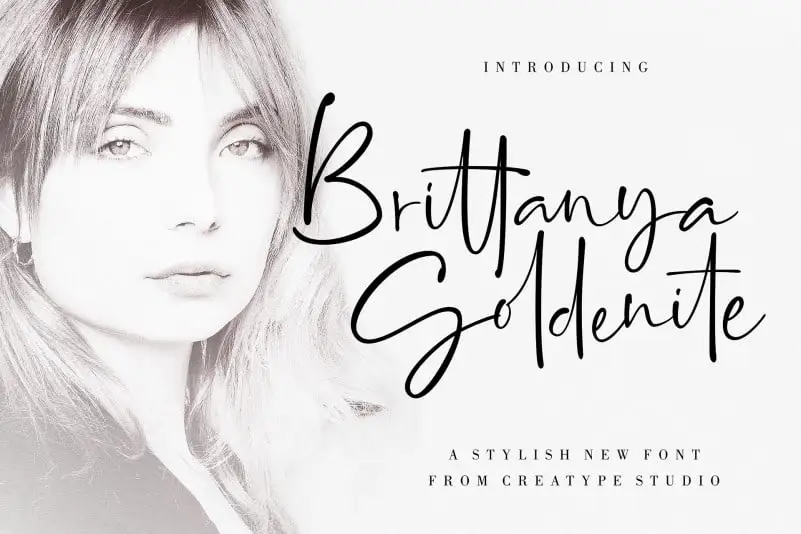
Brittanya Goldenite Script Font – Download Grátis
Brittanya Goldenite Script Font é uma nova fonte de estilo script que oferece uma aparição deslumbrante do formato manual. A escrita tem um toque irregular, mas mantém um brilho elegante e sofisticado. Esta fonte traz um toque autêntico ao seu trabalho, tornando-a perfeita para projetos modernos e sofisticados. Brittanya Goldenite Script foi criada por CreatypeStudio com um design fashionista e sofisticado que se destaca pela elegância clássica. Suas linhas finas e curvas suaves oferecem uma textura única, ideal para adicionar um toque moderno aos seus trabalhos, elevando-os a um novo nível de classe e sofisticação.